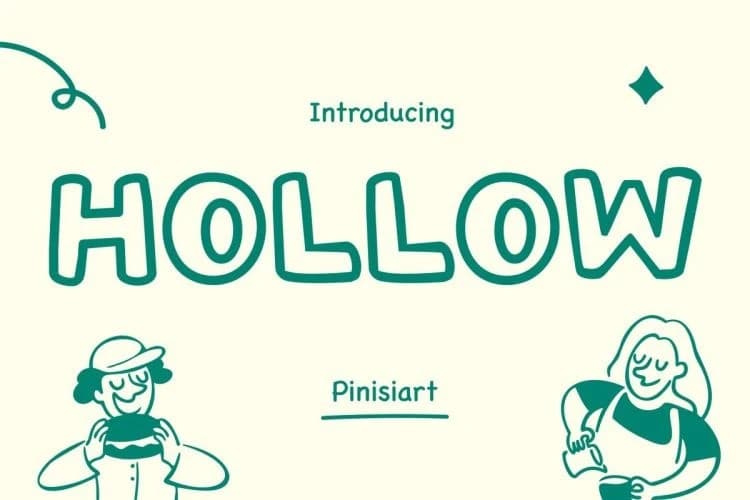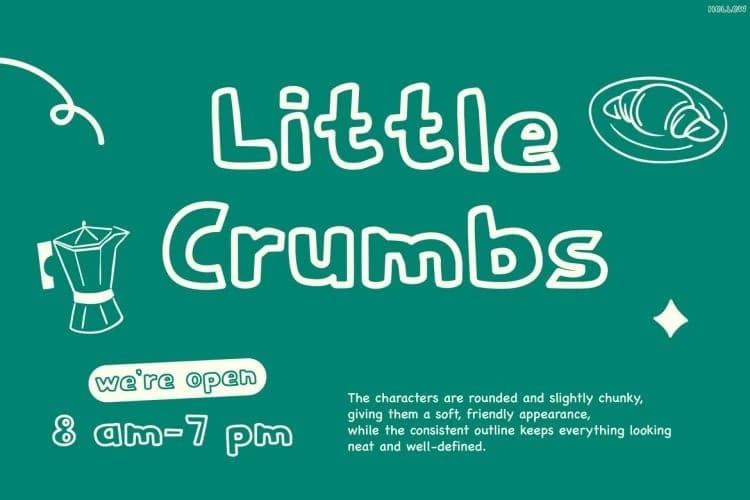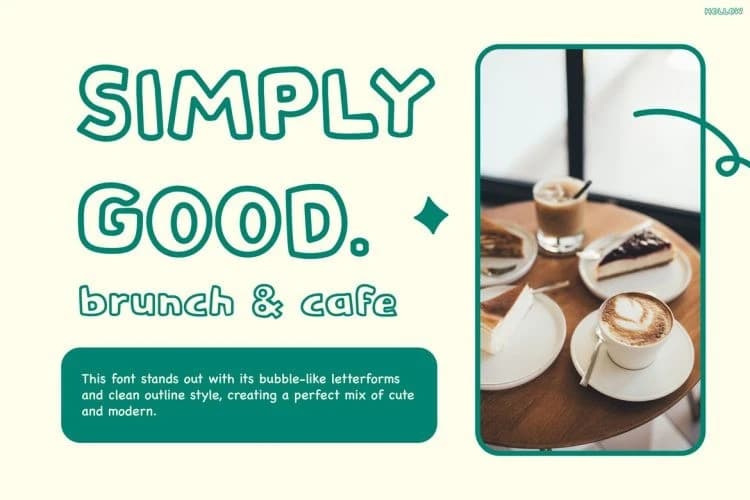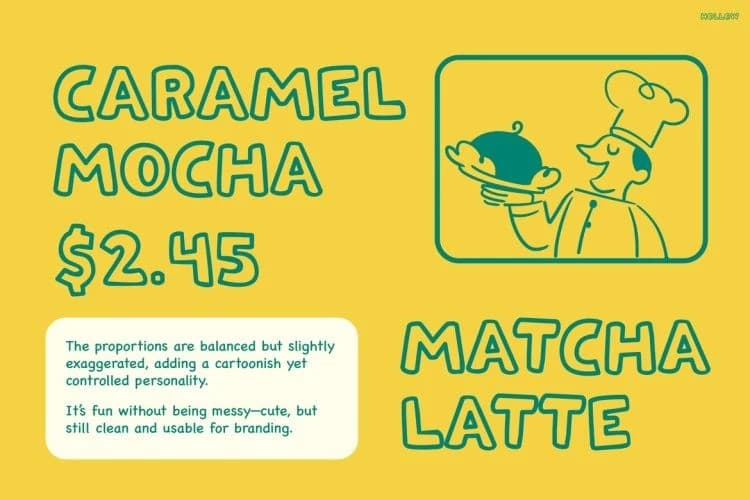
Hollow Playful Font
Hollow Playful Font, oyunbaz balon biçimli şekilleri temiz, minimalist bir estetikle birleştiren çekici bir kontur stilinde yazı tipidir. Ayrıca boş harf formları hafif ve havadar bir his yaratır; bu da anında eğlenceli ama modern bir görünüm sağlar.
Hollow Playful Font, oyuncu balon biçimlerini temiz ve sade bir estetikle birleştiren çekici bir kontur yazı tipidir. Ayrıca içi boş harf biçimleri hafif ve havadar bir his yaratır ve bu da hemen eğlenceli, fakat modern bir görünüm sağlar.